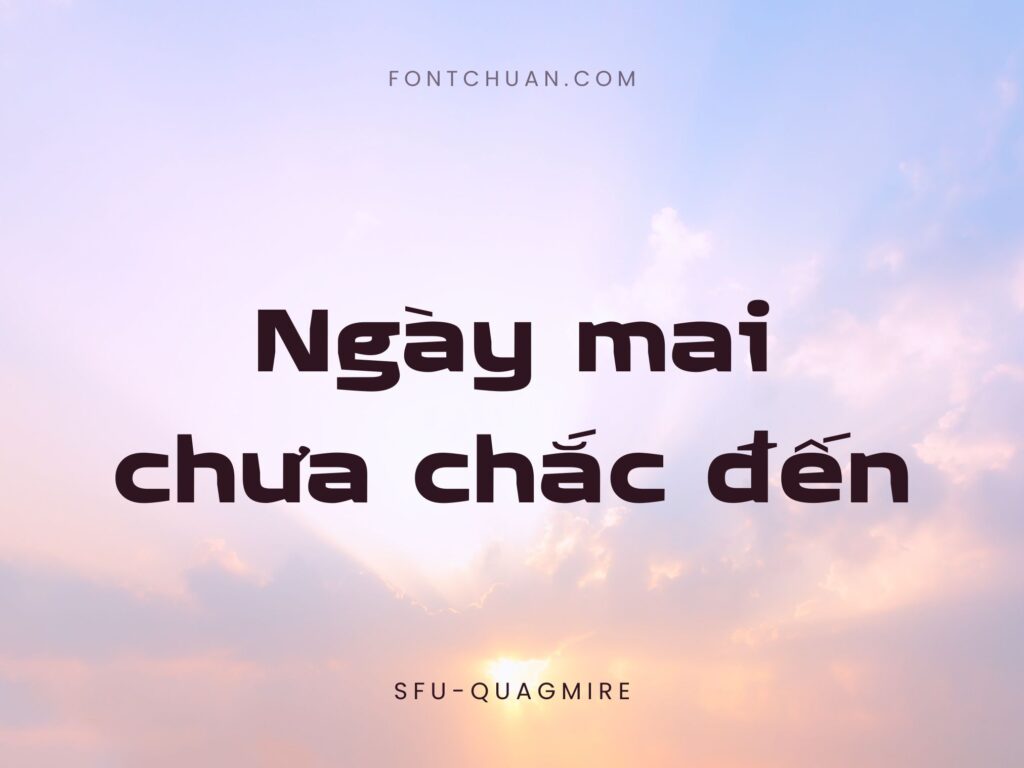
Quagmire là một Font Sans serif hiện đại, được thiết kế bởi Rian Hughes và phát hành thông qua Device Fonts. Font này nổi bật với thiết kế sạch sẽ, sắc nét và tươi mới, mang lại sự linh hoạt và dễ đọc trong các đoạn văn dài. Nhờ sự cân đối và tính ứng dụng cao, Quagmire không chỉ phù hợp cho thiết kế văn bản mà còn trở thành lựa chọn lý tưởng làm Font logo và Font chữ quảng cáo, giúp sản phẩm thiết kế nổi bật và chuyên nghiệp hơn. Với những đặc điểm này, Quagmire có thể đáp ứng nhiều mục đích sử dụng khác nhau.
Về mặt thiết kế, Quagmire có các đường nét rõ ràng và cân đối, tạo cảm giác hiện đại và chuyên nghiệp. Font này hỗ trợ nhiều ngôn ngữ và bao gồm các ký tự đặc biệt, giúp người dùng dễ dàng tùy chỉnh theo nhu cầu. Quagmire thường được sử dụng trong các thiết kế nhận diện thương hiệu, tài liệu quảng cáo, và truyền thông kỹ thuật số. Các ngành nghề như quảng cáo, công nghệ, giáo dục và bất động sản có thể tận dụng kiểu chữ này để tạo dấu ấn đặc biệt trong truyền thông.